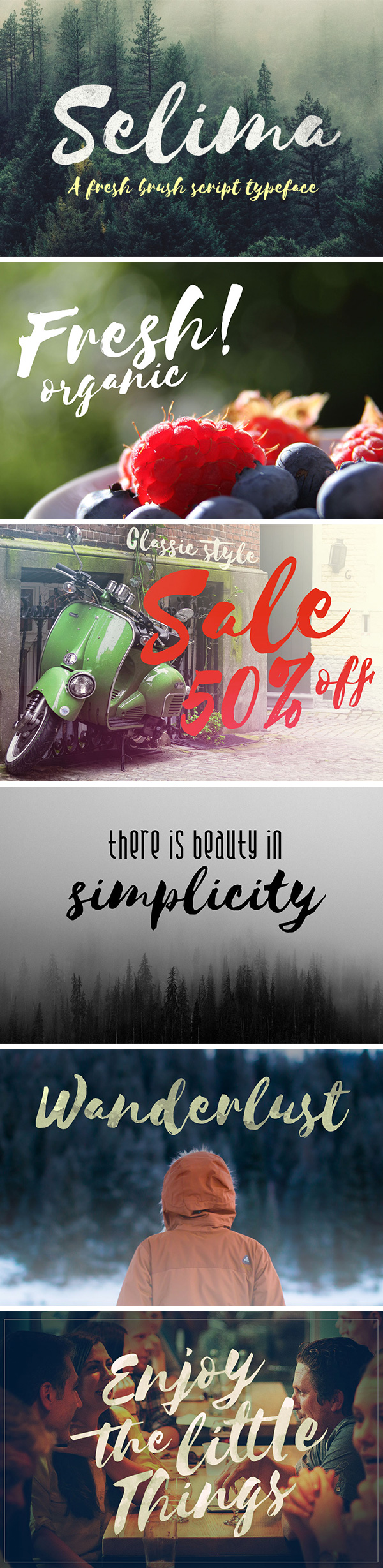
Os dejo una preciosa tipografía de estilo pincel que queda muy bien con fines decorativos o para algunas cabeceras. La licencia es libre así que podéis utilizarla tanto para proyectos personales como comerciales. Para descargarlo pulsad sobre la imagen o en el link del pie de la entrada. Espero que os sirva y recordad que los like y los follow ayudan mucho así que visitadnos en Twitter y Facebook. También nos podéis encontrar en Flipboard buscando nuestra revista El Arquitecto de Ilusiones.